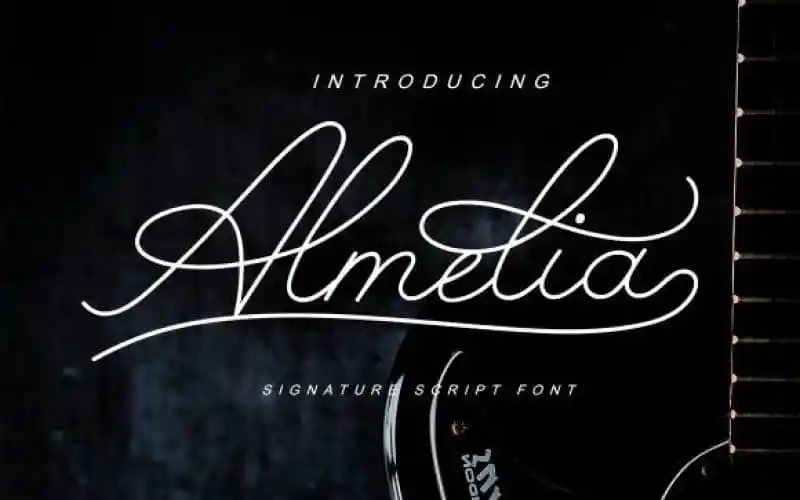
Almelia Handwritten Font – Fonte Grátis
Almelia Handwritten Font
A fonte ‘Almelia Handwritten Font’ é uma escolha perfeita para aqueles que buscam elegância e naturalidade em cada projeto. Com seu traço monolíndico suave, essa fonte não apenas adiciona um toque pessoal a seus designs, mas também se ajusta perfeitamente a várias categorias de trabalho. Suas linhas delicadas são ideais para criações de casamento ou outros eventos especiais, como carteirinhas de bolo personalizadas. Ela é também uma excelente escolha para materiais de branding e identidade visual que precisam de um toque suave e inconfundível. A fonte ‘Almelia Handwritten Font’ também se destaca por seus usos criativos, como stickers infantis, cartões personalizados para negócios ou casamentos, citações em redes sociais com estilo tipográfico, esboços de moda elaborados, e desenhos de amor a cores que encantam. Suave mas poderosa, a ‘Almelia Handwritten Font’ oferece uma variedade infinita de possibilidades para estilistas, designers de conteúdo digital e criativos em geral. Seja para criar um design elegante ou um gráfico minimalista, essa fonte é certamente o caminho certo.